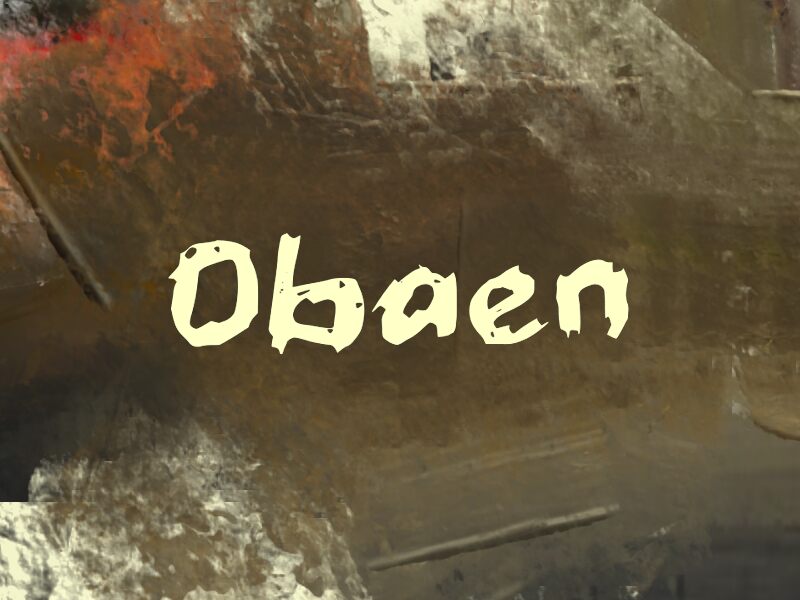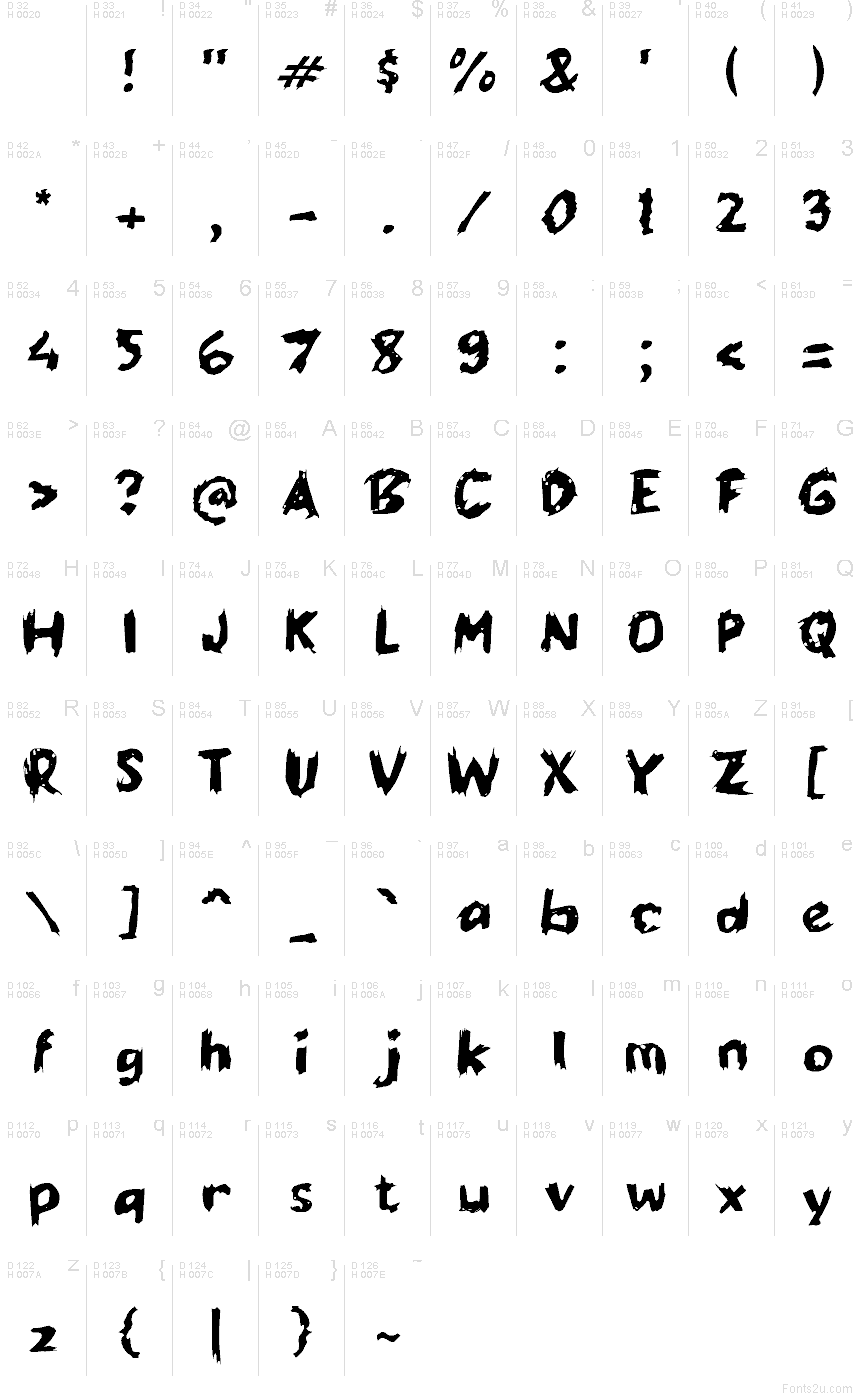
Obaen
Obaen de Wep es una tipografía de pincel gratuita, definida por siluetas oscuras, como de tinta, y muescas afiladas que hacen que las letras parezcan cortadas más que pintadas con suavidad. Sus bordes rugosos y los espacios irregulares en su interior crean una textura desgastada, dándole al diseño una presencia cruda y hecha a mano, lejos del ritmo de una tipografía script pulida.
Esa superficie raspada y de alto contraste funciona a la perfección en títulos para pósteres, arte de álbumes, gráficos de streetwear, encabezados de juegos y empaques con temática de terror, donde la textura irregular ayuda a construir la narrativa visual. Las líneas cortas de branding y los volantes de eventos también se benefician de sus formas contundentes y dañadas, que aportan un toque de realismo sin necesidad de añadir efectos de desgaste adicionales.